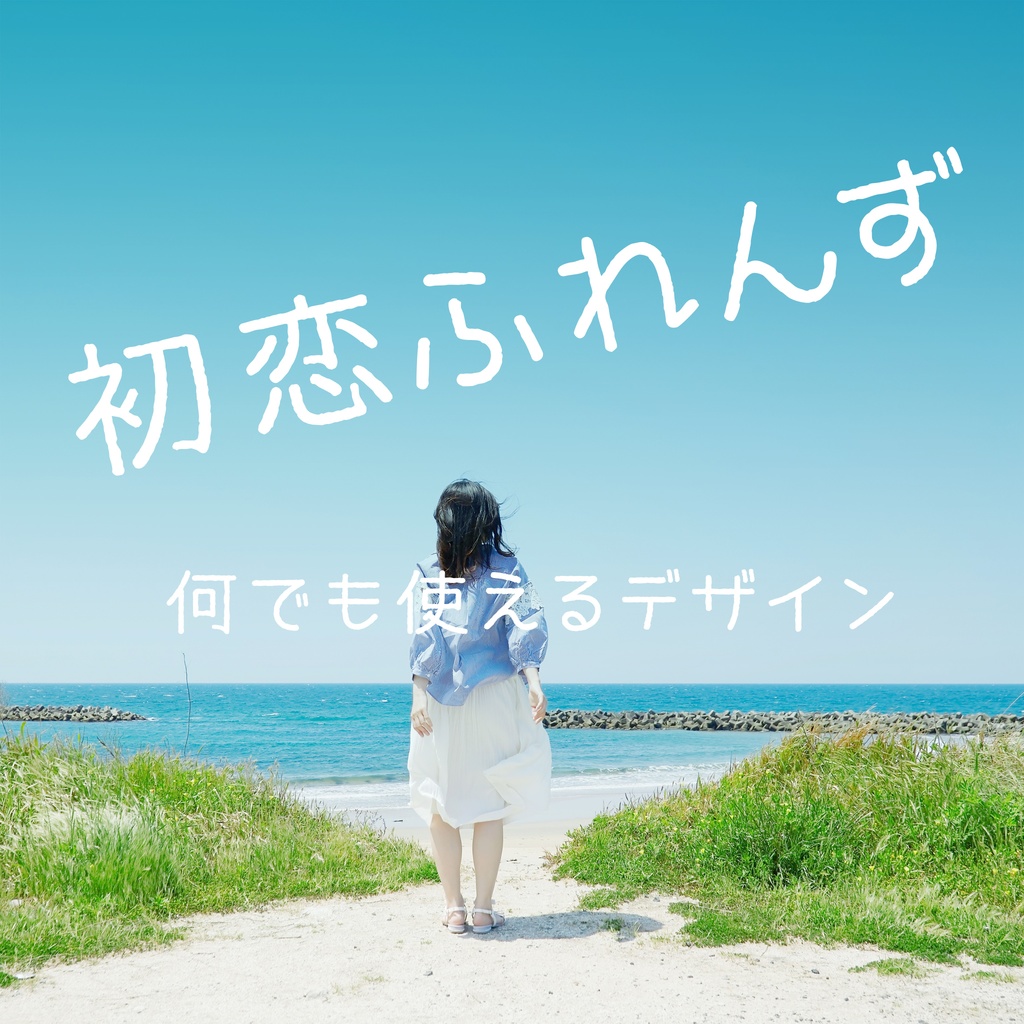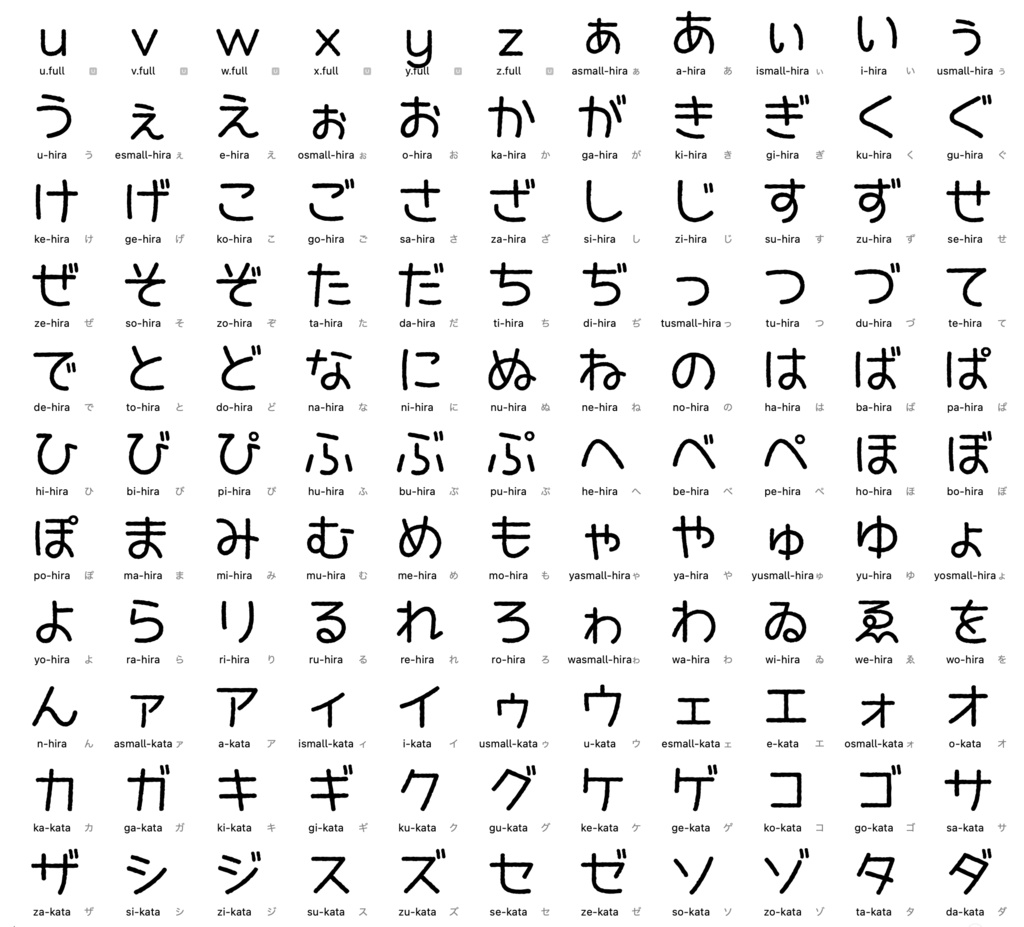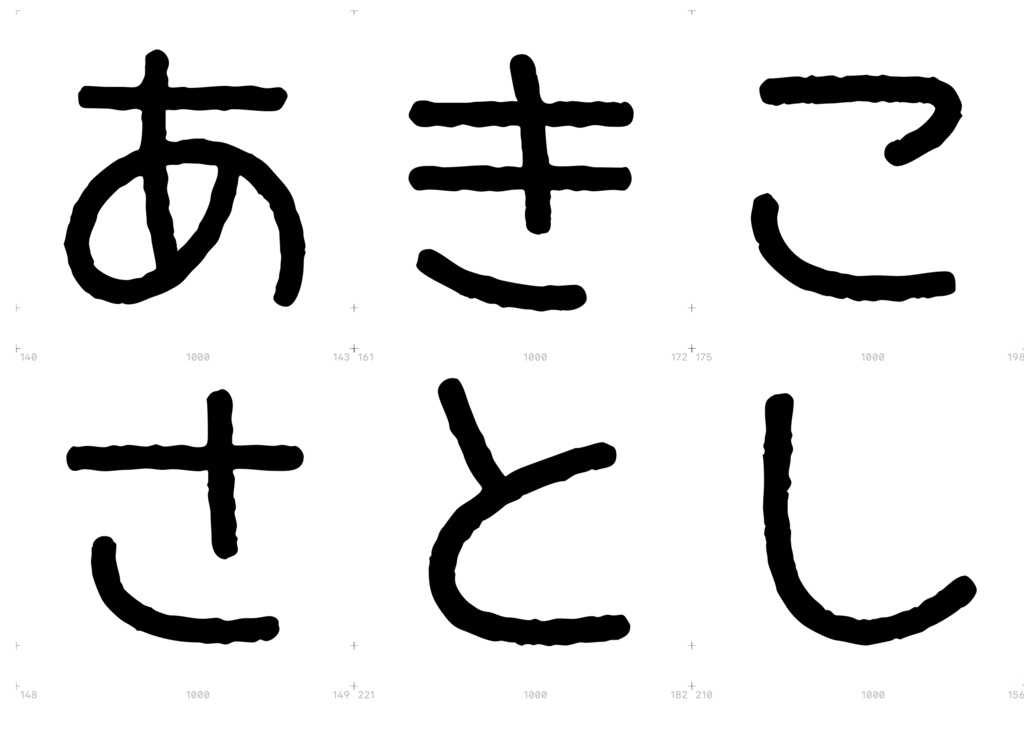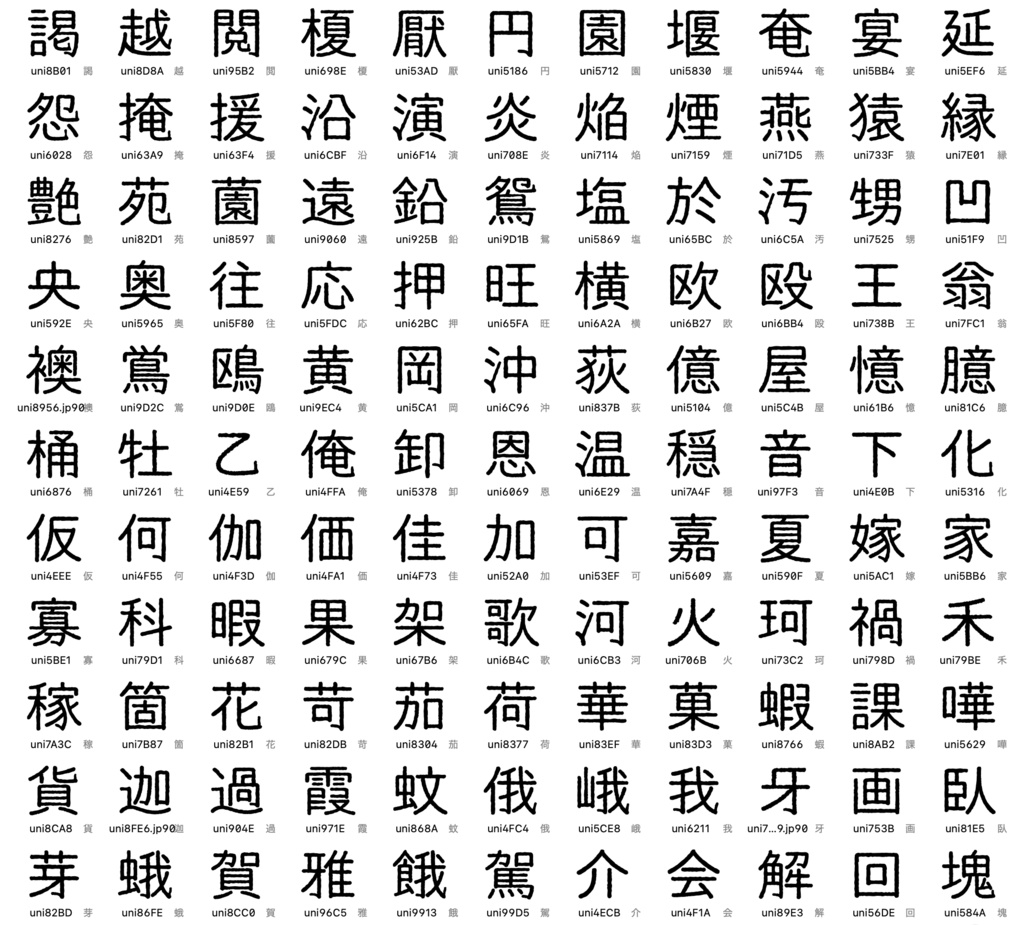
初恋ふれんず フォント
フォント名:初恋ふれんず 少女漫画のモノローグに使えそうなカワイイ系の書体です。アウトラインを少しガタガタさせてラフな雰囲気にしつつ、ほどよく読みやすくて、使いやすいデザインにまとめました。収録文字数4,072文字 動作環境 Mac:システム/OS X対応(10.x)〜最新のOS X Windows:OS/日本語版Windows2000、XP、VISTA、Windows7〜11以降 安心して使えるロイヤリティフリーの書体 製品版はあらゆる商用・デザイン用途(印刷物・ゲーム・アプリ・映像・動画・ロゴ・同人作品)に使用できる、商用申請の必要のないロイヤリティフリーの書体になります。収録文字数4,072文字になり、第一水準の漢字2965字と第二水準のよく使う漢字460字、記号類・約物・キリル文字・半角カタカナ等647字 が含まれています。 個性的なデザインに注目した日本語フォントのダウンロード販売。物語の奥行きを感じさせるセンスの良いフォントは、あなたのデザインに深みとおもしろみを与えます。安心して使える商用利用可のオリジナルフォントです。